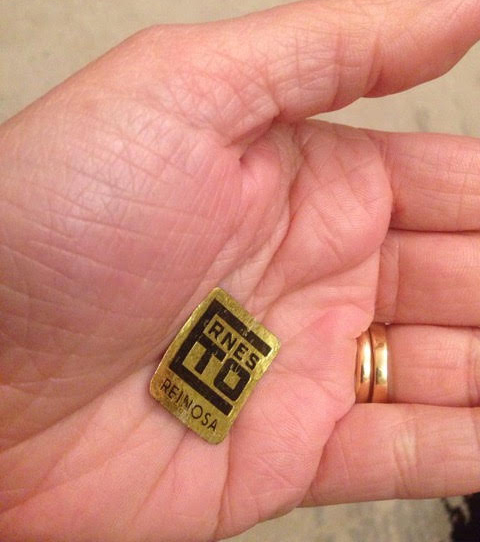
Mercería Ernesto. Reinosa
Tras la publicación del post sobre Noval y la conexión Santander – Reinosa, llegó a Santatipo un correo dando las primeras pinceladas de uno de los Rótulos. Gracias a Neila Campos, bisnieta de Ernesto López, descubrimos un poquito más la historia de la «Mercería Ernesto» en Reinosa.
Foto en la que se ve que el edificio servía como soporte para distintos anuncios y que era conocido como el “Tablón de Chirigata”. Historia y foto compartida por Jesús Allende Valcuende (Porende Estudio Gráfico).
El rótulo data de 1950, cuando la mercería fue traspasada a Pepita López y Aurelio Campos, quienes le pusieron el nombre de Ernesto, el padre de Pepita. En 1977 se traspasó nuevamente; una de las cosas que más llama la atención del rótulo es el anagrama «Ernesto». Es una creación del propio Ernesto, y según nos dice su familia, en los años 30 lo utilizó para un identificar gráficamente un comercio suyo de ultramarinos (ya desaparecido) y por otro lado, también lo utilizó  como Ex libris y como firma de los cuadros que pintaba sobre paisaje campurriano. Nos cuentan también, que curiosamente y con el paso del tiempo, la gente que no conoció a Ernesto, empezó a referirse a la mercería como «Novedades» porque no entendía el significado del anagrama.
Lo que se ve aquí es una antigua «pegatina» publicitaria que aún se conserva, pero que se pegaban con pegamento, no eran autoadhesivas